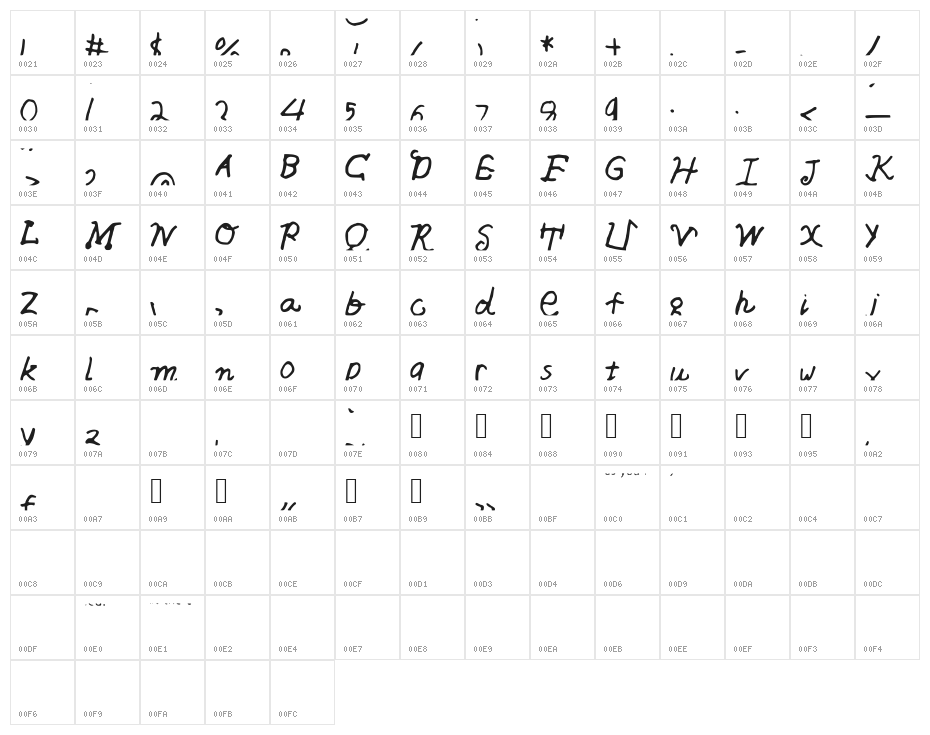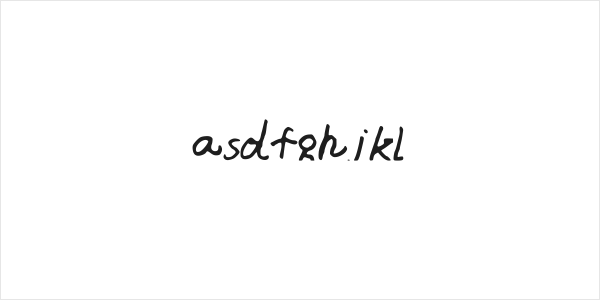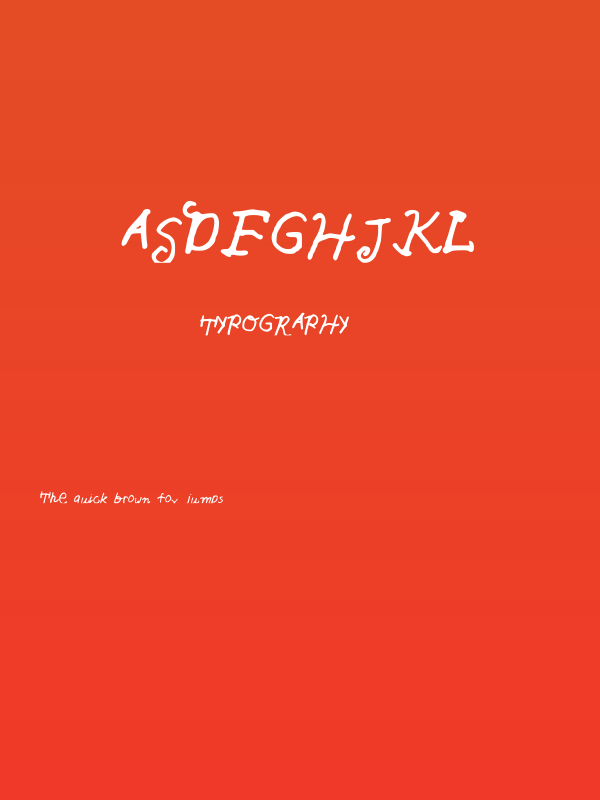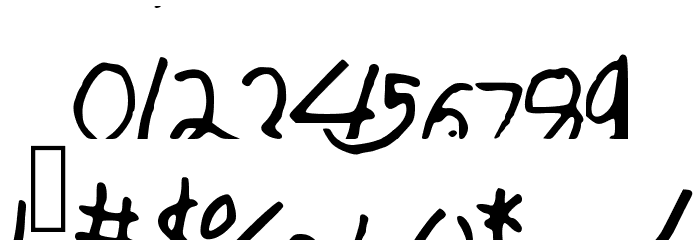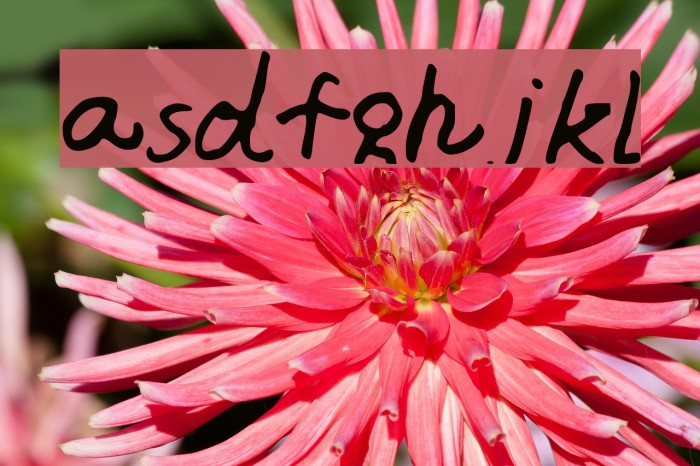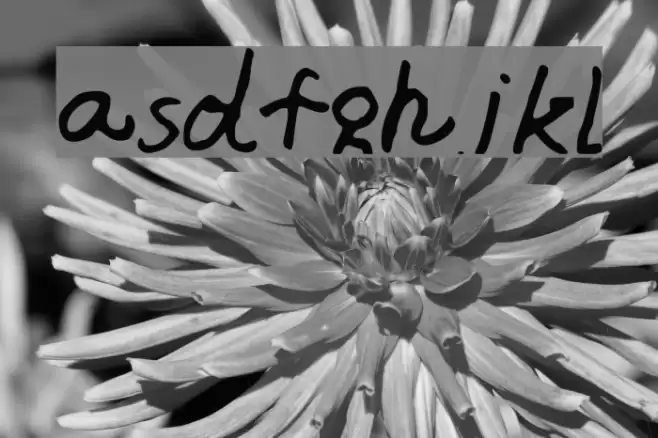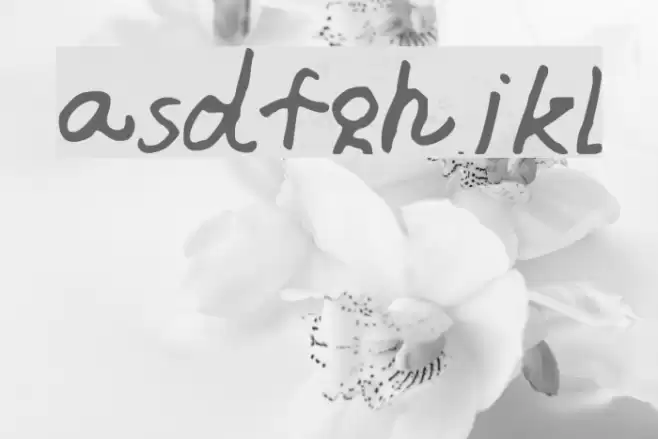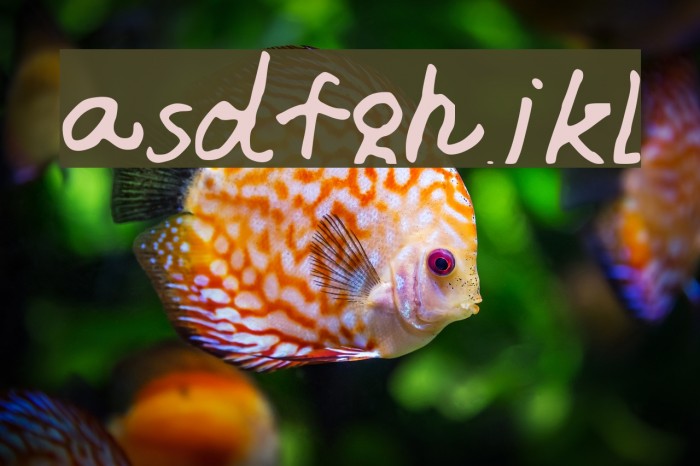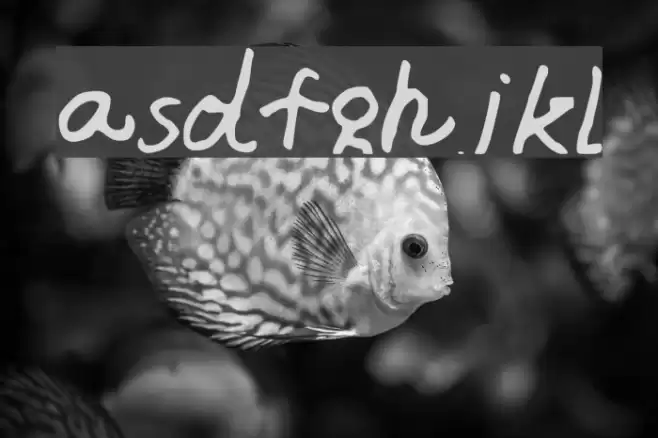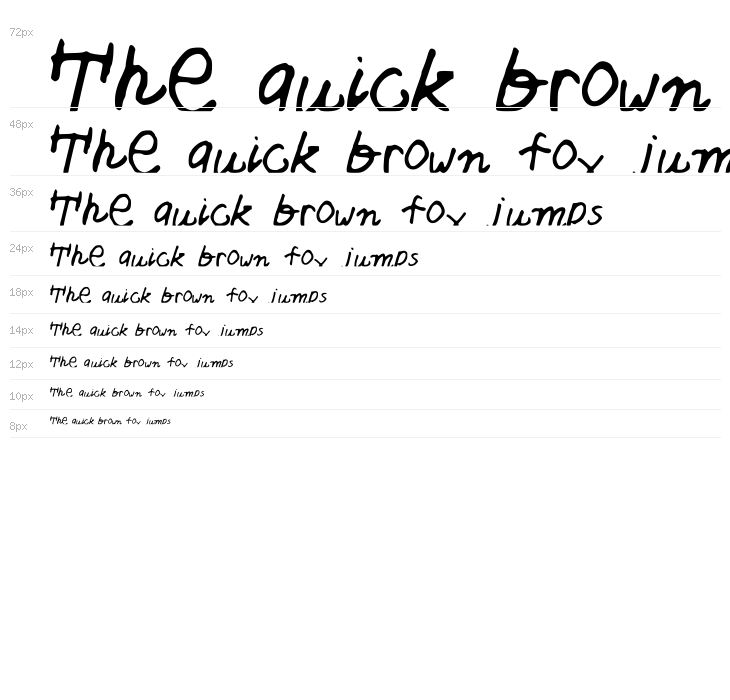
asdfghjkl Font
| Gesamtstil | Casual |
| Anwendungsfall | Headlines, Logos, Informal Text |
| Vorgeschlagene Projekte | Ideal for greeting cards, children's books, casual invitations, and personal branding. |